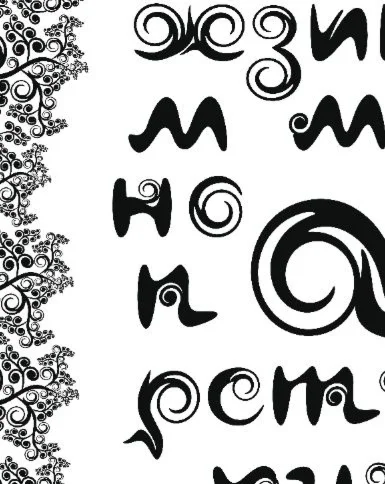
Кириллический декоративный шрифт, все буквы русского алфавита. Буквы, составленные из черно-белых завитков, для оформления различных дизайнерских проектов. Курсивные строчные буквы. Прямая ссылка для скачивания архива, в архиве векторные файлы eps и cdr, а ракже растровые файлы: jpg высокого разрешения без сжатия и файл png c прозрачным фоном.